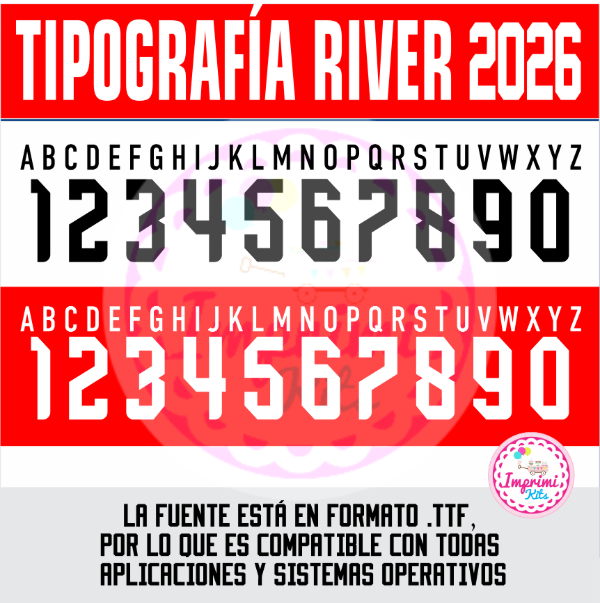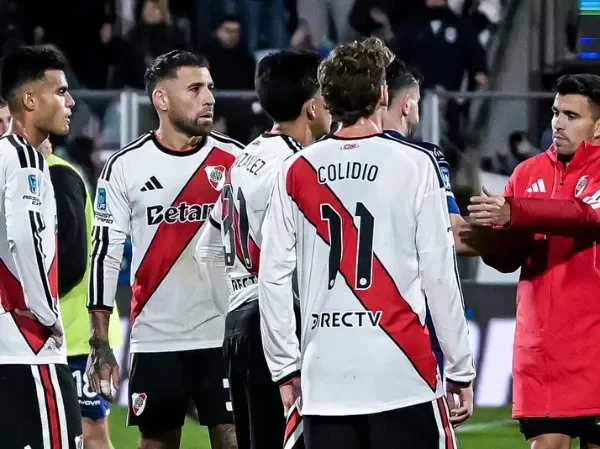
NUEVA! Tipografía Números Fuente Camisetas 2026 RIVER CAMISETA TITULAR
Tipografía Números Fuente 2026
Realizá todo tipo de creaciones con la tipografía utilizada actualmente en el club